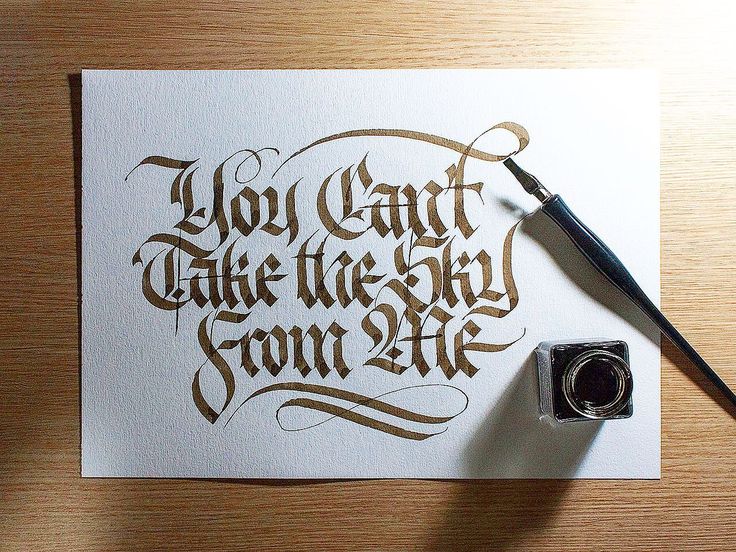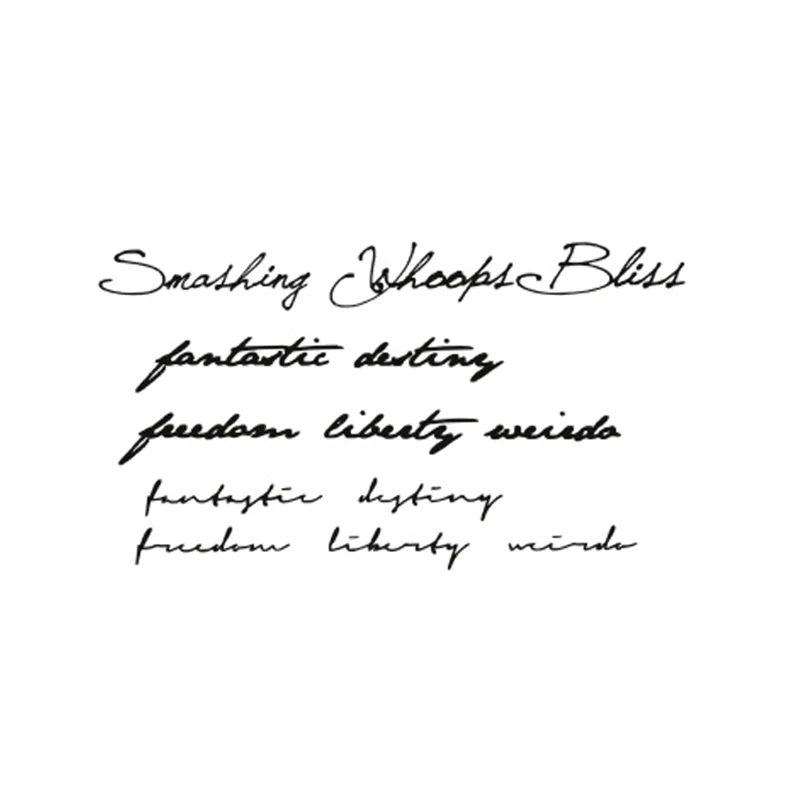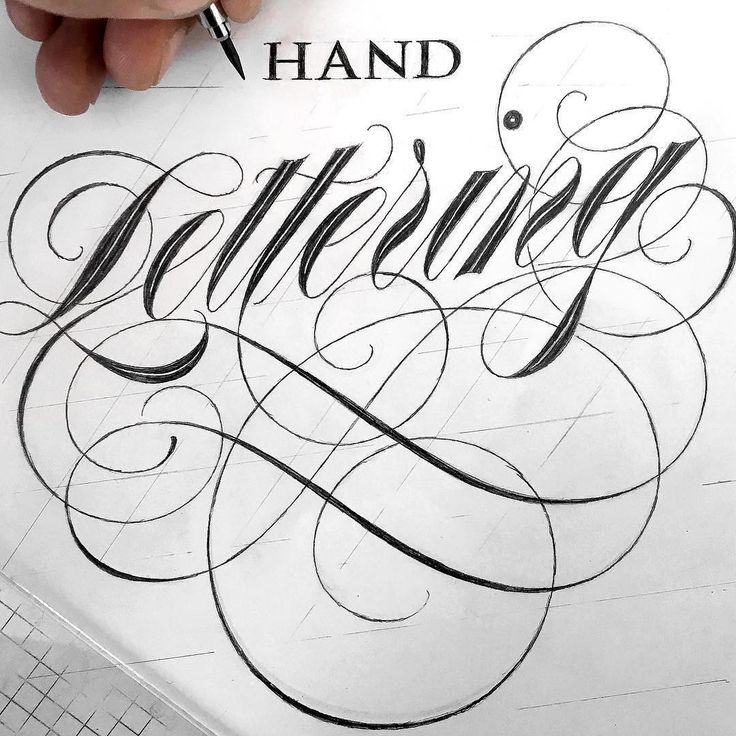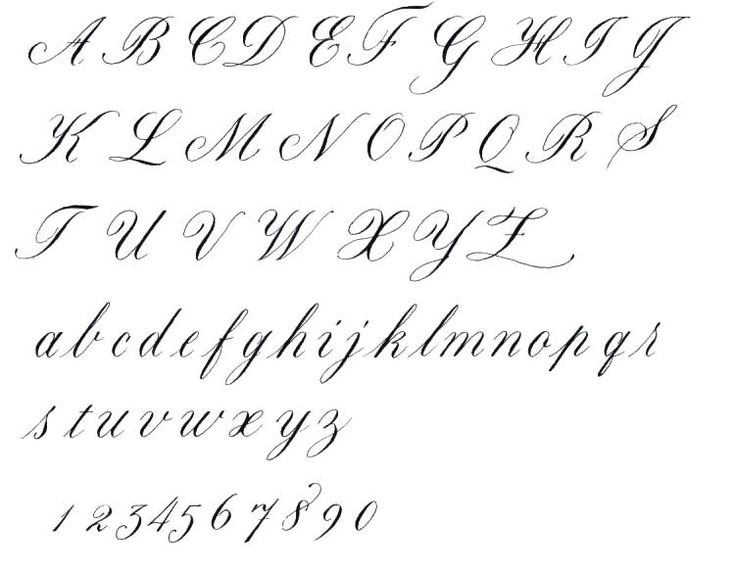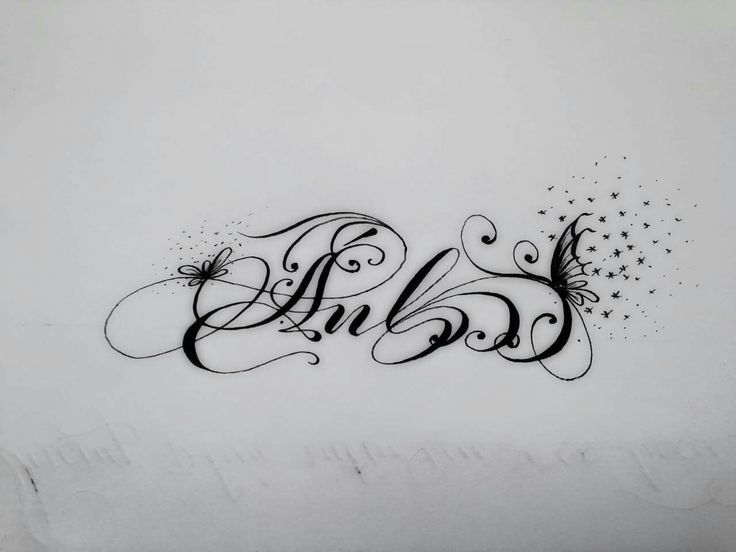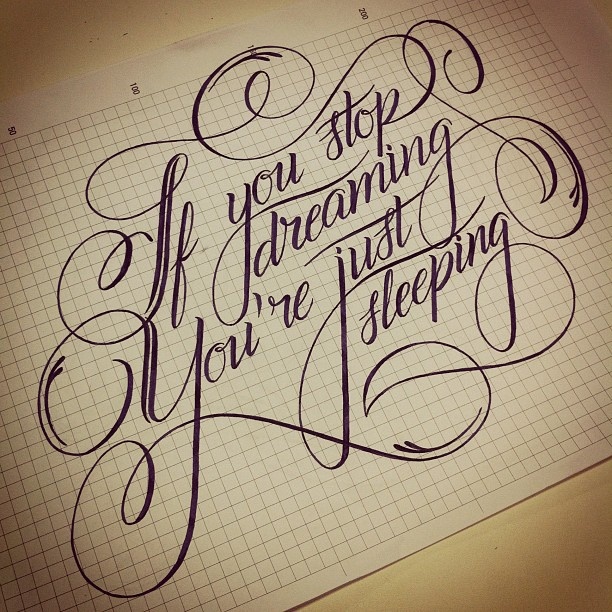
Шрифты для тату: как подобрать подходящий
Татуировки с текстовыми надписями – уже давно полюбившийся тренд среди большого круга людей. Многие хотят запечатлеть любимую фразу, крылатое выражение или кредо всей жизни на собственном теле, как талисман и защиту от несчастий.
Характер и вкус владельца тату можно прочесть не только с помощью текста, но и через оформление. Шрифты для тату и размер фразы на теле демонстрируют его индивидуальность.
Шрифт и текст надписи для своей татуировки вы можете выбрать любой.Популярные шрифты с примерами на фото
Красота и изящество леттеринга состоят в выдержанности стиля, четкости линий и филигранности каждой буквы, которые предполагается в точности воссоздать на коже человека с распечатанного эскиза. Применение инструментов графики в искусстве тату позволяет создавать на коже шедевры рукописного, печатного или художественного письма.
Выделяют следующие виды шрифтов для тату:
- готический;
- кириллический;
- этнический;
- граффити;
- старая печатная машинка.
В рамках заданного стиля мастер способен подобрать одну из множества вариаций шрифтов по готовым каталогам или сгенерировать готовую фразу в любом из представленных стилей на специализированном сайте. Подборка подобных фото ниже.
Рукописный
Прописные и строчные литеры – классический стиль в каллиграфии, знакомый многим со школьной скамьи. Существует большое количество вариаций стиля, который можно адаптировать под почерк того или иного мастера.
Главными свойствами шаблонной рукописи являются округлые формы, завитки и соответствие букв нормам типографики данного языка. Для арабского наречия характерна размашистость, мелкие символы, обилие точек и слитное письмо.
А для славянских или романских алфавитов – раздельное написание литер, умеренно строгие, но при этом плавные линии.
Классическое начертание букв подходит для татуировки фраз великих мыслителей, цитат из стихотворений и романов.
Латинский
Надпись на латыни без перевода на русский язык символизирует желание владельца татуировки завуалировать точный смысл фразы, оставив благозвучный оригинальный вариант.
Латинские фразы емкие по смыслу, для них подходят красивые сдержанные шаблоны с использованием простых форм и линий, отображающих содержание надписи. Для мужских и женских вариаций шрифт может различаться, быть более плавным, растянутым по строке или наоборот – строгим, с острыми углами.
Фразы на латинском.Кельтский и готика
Тексты на латыни сочетаются с готическим шрифтом и эстетикой, которая является одной из классических в искусстве татуажа. Для татуировок характерны размашистое начертание литер с декоративными элементами и эффект бликов и старения на литерах. Написание букв в подобном стиле встречается в староцерковных текстах и печатных изданиях под старину.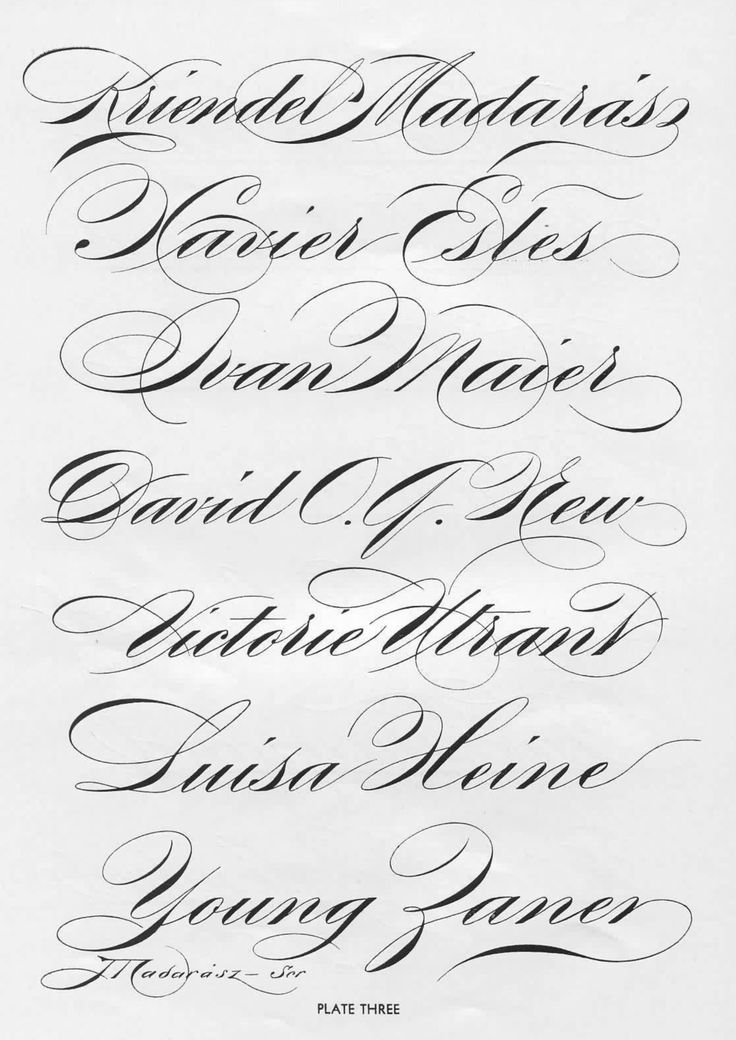
Беспорядочное граффити
Стиль граффити в тату выражается как абстракция, содержащая 1 слово или фразу, которую часто сложно прочесть с первого раза из-за витиеватости и излома линий.
Изображения в урбанистическом оформлении, встречающиеся на стенах домов в городах, просто создать в точной копии на теле человека.
Литеры прорисовываются внахлест друг с другом и часто внешне больше напоминают рисунок, ребус или схематический узор, чем связное слово. В этом состоит его особенная черта, выражение бунтарства и взгляда на реальность под другим углом.
Текст выполнен в стиле графити.Другие варианты
Вышеперечисленные шрифты можно условно подразделить на подкатегории – древнеславянский, кириллический, фактурные шрифты с применением декоративных техник и иероглифический под стилистику письма древних времен.
Текст разных размеров и разным шрифтом.Буквы могут быть закрашены не полностью, прописываться под наклоном, иметь мозаичное начертание, электронное написание, округлый объем в зависимости от пожеланий заказчика.
Как выбрать и не ошибиться
Татуировка наносится на кожу на всю жизнь, поэтому основным критерием подбора фразы и шаблона для ее исполнения являются исключительно эстетические предпочтения человека.
Проверить внешний вид можно на этапе составления эскиза рисунка-надписи: ее можно приложить на область нанесения и мысленно представить величину, угол наклона и интенсивность заливки букв цветом. Если один из пунктов не устраивает или есть сомнения, лучше не рисковать и поискать новые варианты.
Онлайн-подбор шрифта
Услугу подбора шрифта для тату онлайн-подбор включают в стоимость процедуры. После заказа фразы в нужном оформлении эскиз приходит на электронную почту автора. Надпись можно сгенерировать неограниченное количество раз исходя из количества понравившихся шрифтов.
Заключение
Ваш опытный татуировщик сможет мастерски скопировать почерк и вытатуировать его на вашей коже на память. Старайтесь никогда не копировать работы других художников. Если вы не уверены в том, какой стиль или размер шрифта использовать, запишитесь на консультацию к своему художнику и обсудите идею, которая у вас может возникнуть.